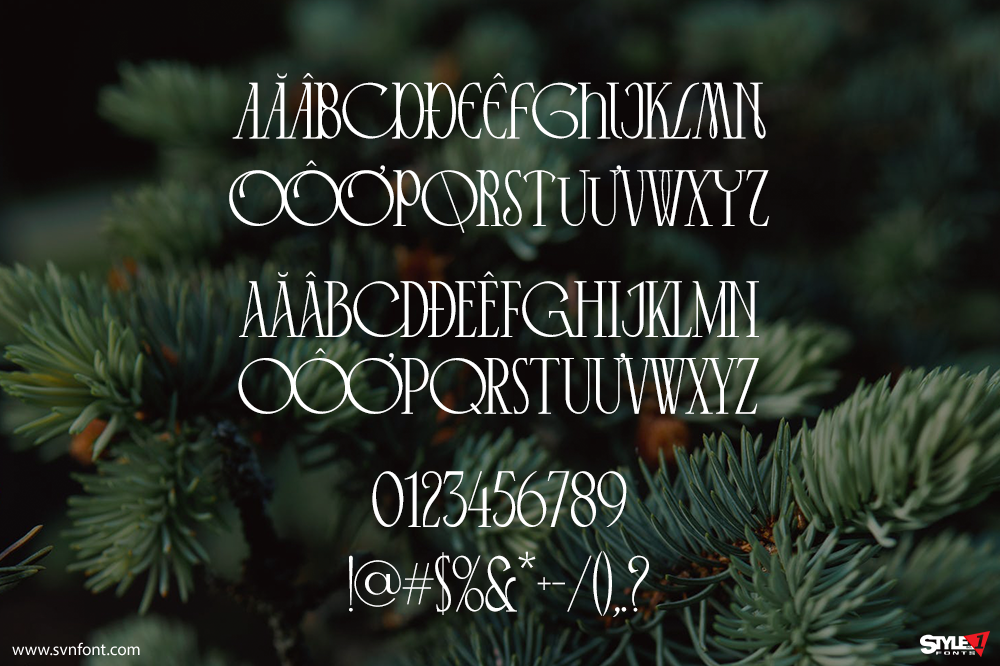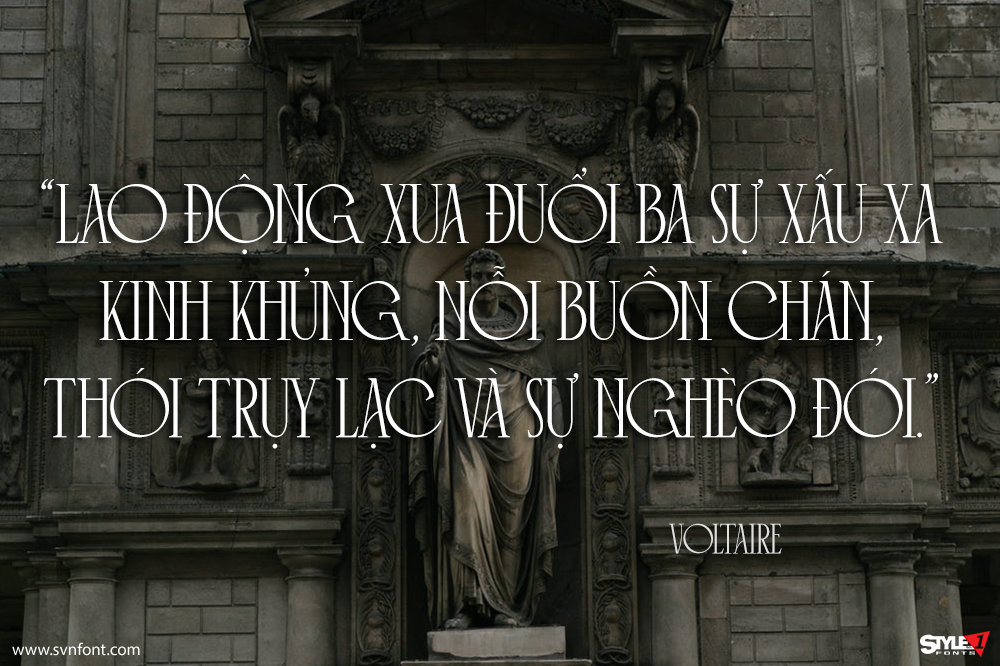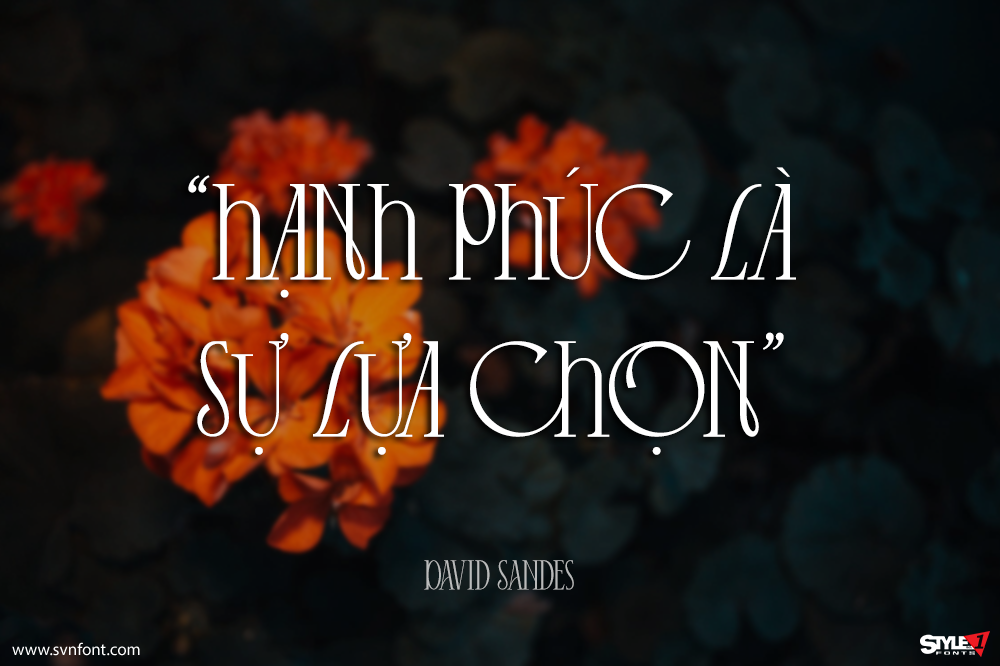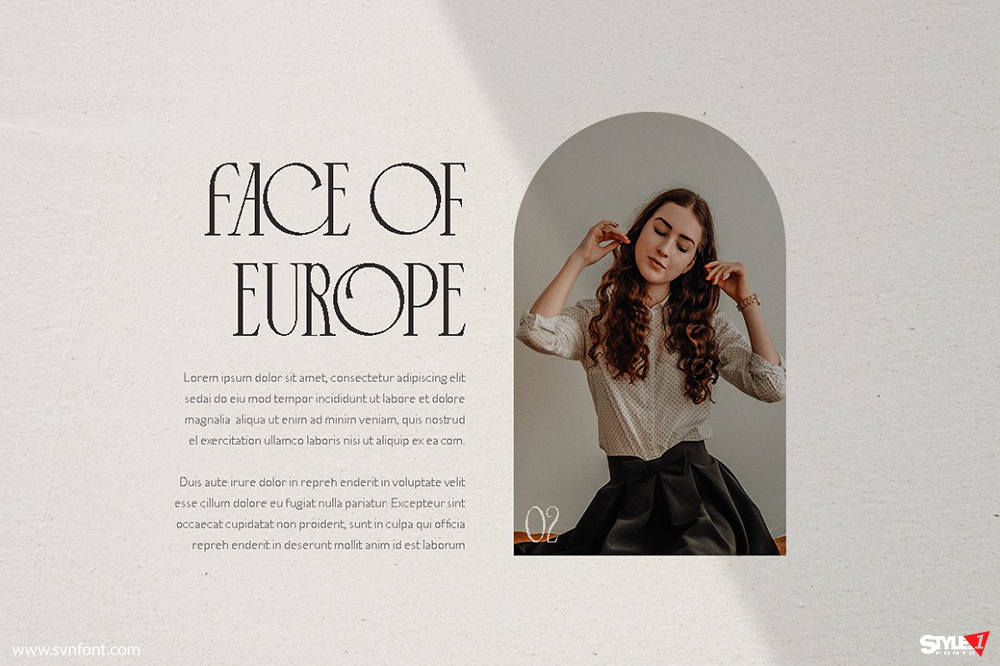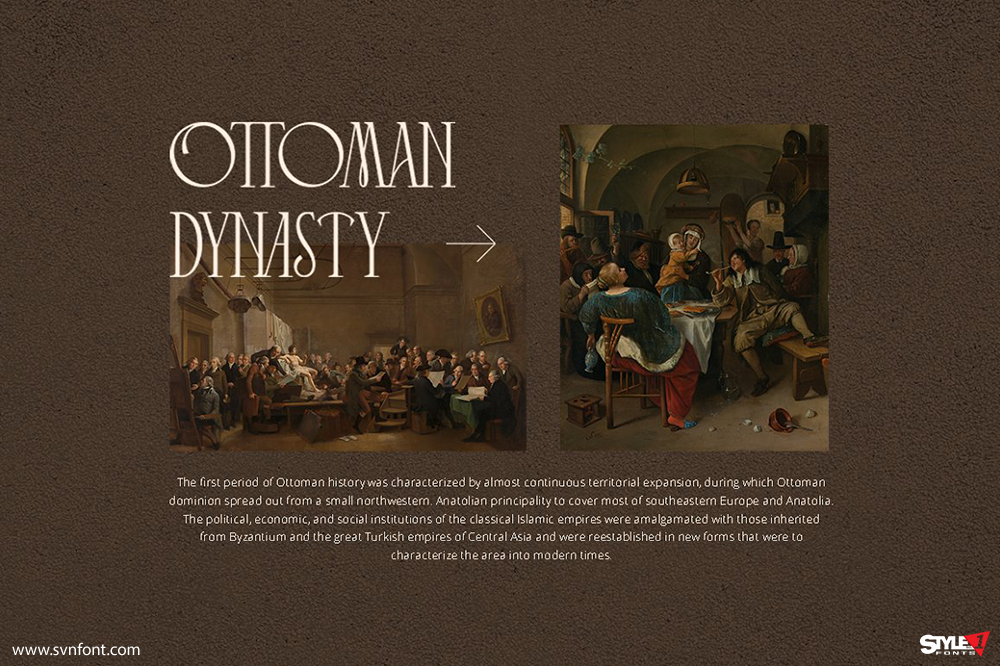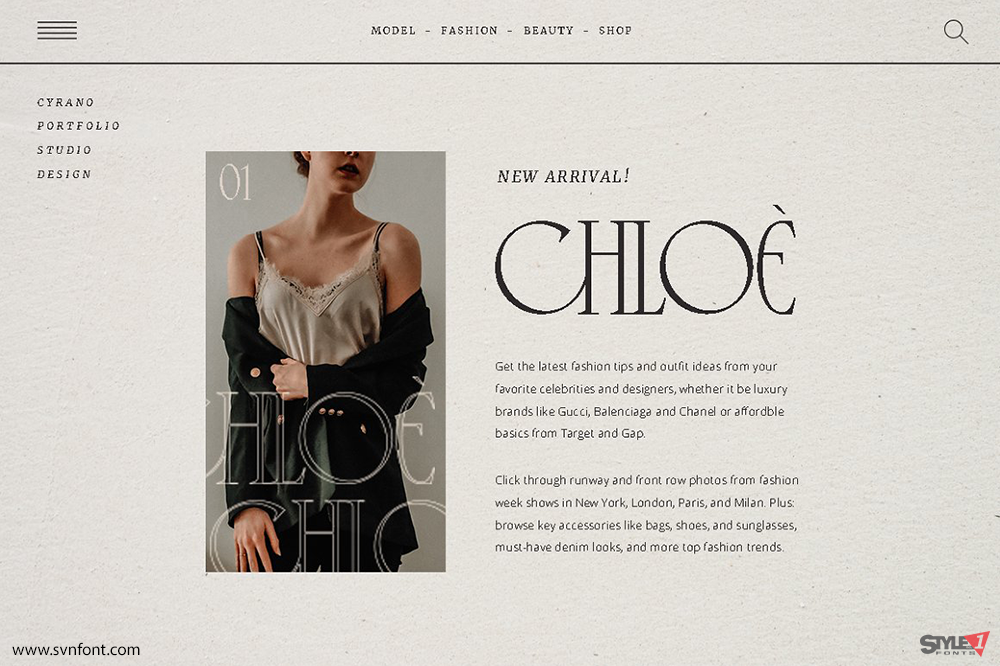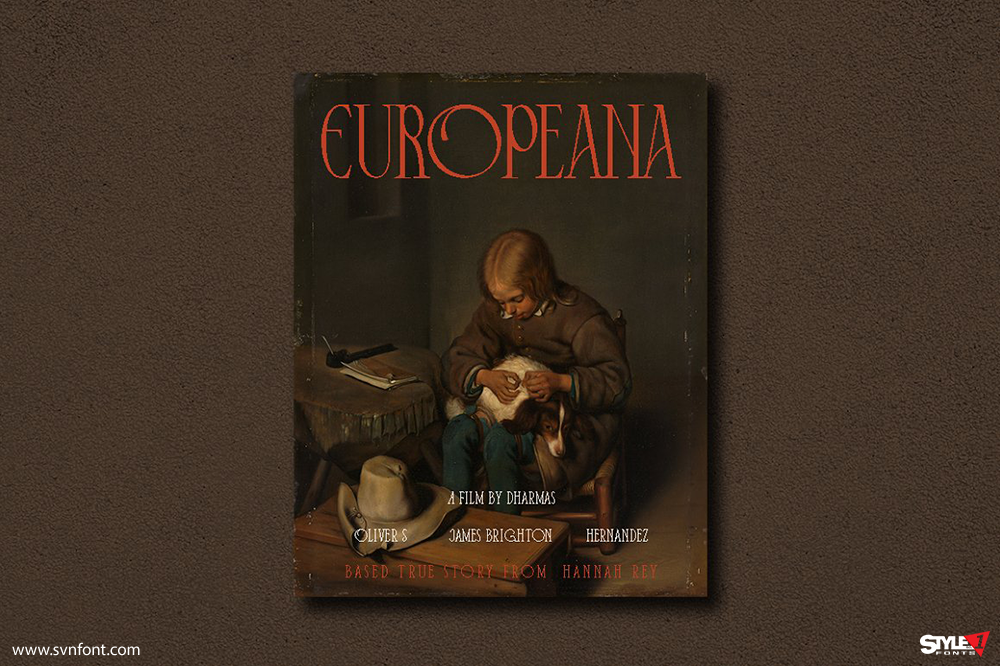
Cyrano là một serif độc đáo, nơi từng ký tự được trau chuốt kỹ lưỡng để mang lại diện mạo thời trang đậm chất châu Âu. Typeface này được thiết kế đặc biệt cho các dự án mang chủ đề fashion, rất phù hợp với logo, tiêu đề, tạp chí và các thiết kế lifestyle sang trọng, chic.
Điểm thú vị của Cyrano là chữ thường chính là dạng chữ hoa, còn chữ hoa là các alternate — bạn có thể thay đổi biến thể chỉ bằng cách gõ chữ hoa, vô cùng dễ sử dụng và linh hoạt.